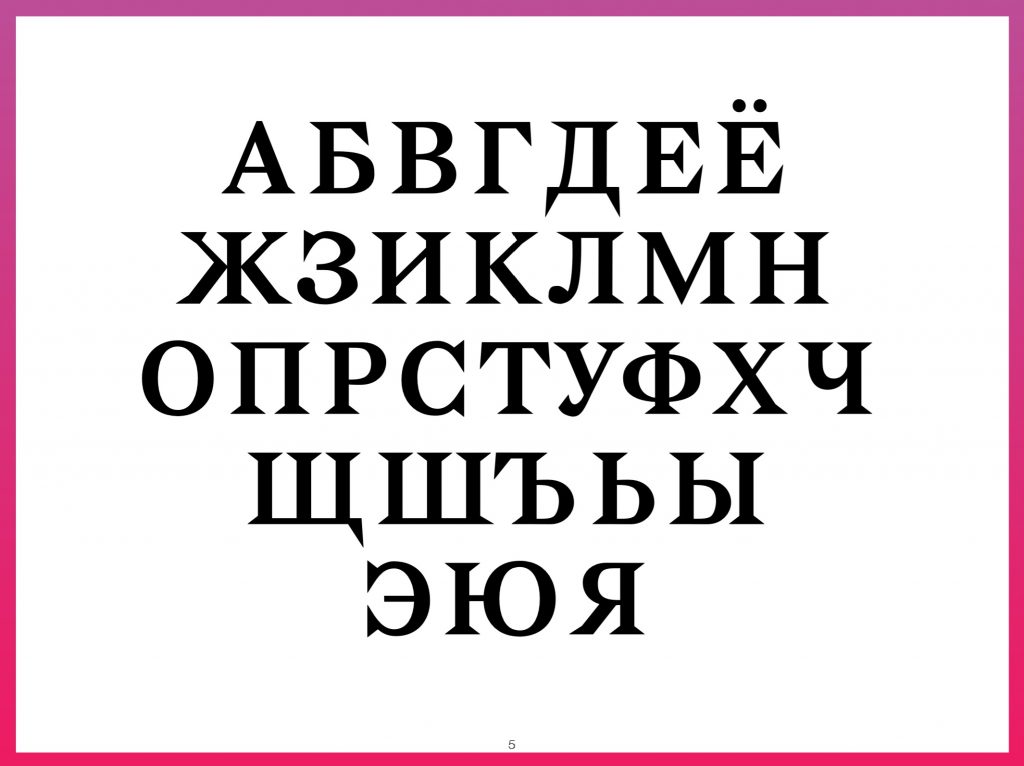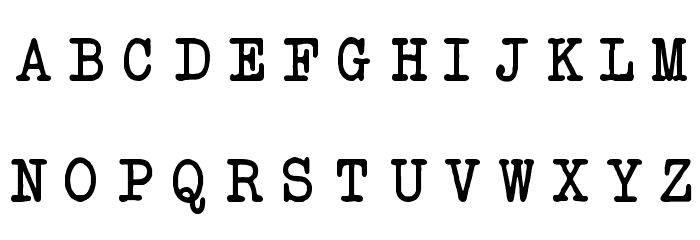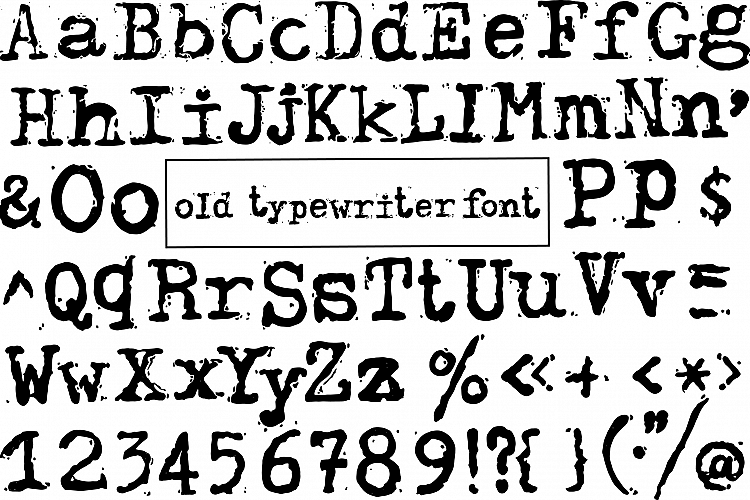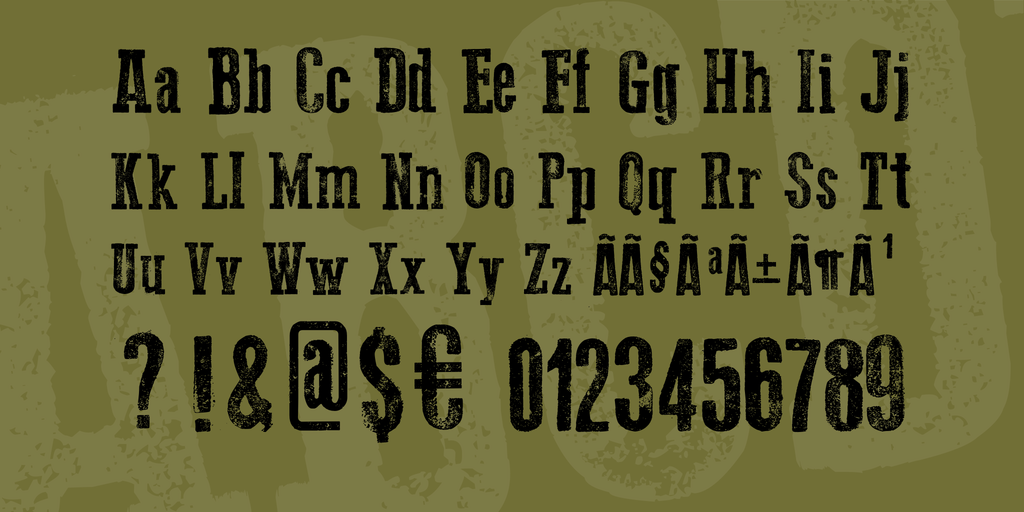
Кириллица печатная машинка шрифт: Кириллические шрифты в стиле «печатной машинки» для Photoshop
45+ шрифтов «печатная машинка» для Word / Фотошопа + машинописные русские шрифты
Название сегодняшних материалов в подборке полностью определяется способом их создания — это шрифты печатной машинкой. Теоретически, по форме и стилистике они должны соответствовать реально напечатанным текстам. Похожий принцип типографики встречался в заметках про граффити или надписи мелом на доске — по данным наименованиям вы сразу четко представляете их внешний вид.
Если говорить о визуальной составляющей, то тут все достаточно тривиально. В целом нет такого разнообразия как в декоративных и оригинальных шрифтах. Варианты отличаются разве что качеством / силой «оттиска» для букв и наличием неких посторонних «вкраплений»: где-то текст получается более четкий, в других случаях он выглядит слабо пропечатанным.
Brother Deluxe 1350
1942 Report
Special Elite
Urania Czech Font
My Underwood Font
Tox Typewriter
Through the Night
Typical Writer Font
Kingthings Typewriter
Traveling Typewriter
Rough Typewriter
CarbonType
Harting
Secret Typewriter
Courier Prime
DK Trashtype Font
Love Letter TW
AFL Font Pespaye Nonmetric
Veteran Typewriter
Есть варианты машинописных шрифтов, которые имеют чуть больше декоративных элементов.![]()
NelsonOldNewsPaper Font
Telegraphem
Old printing press
Subway Novella
Punkbabe
Xerography Font
F25 Blackletter Typewriter
Type Keys
Дополнительно нашли немного кириллических фонтов для рунета. К сожалению, оригинальных картинок с их применением здесь не так много, поэтому размещаем скриншоты с доступными символами алфавита — это даст понимание используемого в них стиля. Очевидно, что машинописных шрифтов на русском гораздо меньше англоязычных, но с десяток точно наберется.
TrixieCyr Plain
Bezpredmetizm
DS Moster
B52
a_OldTyperNr Regular
DS VTCorona Cyr
ABC_TypeWriterRussian
Lettera Trentadue
TypeWriter Normal
Prestige-Normal Regular
Vector Old Typewriter Font
Vintage Grunge Typewriter Letters
Alphabet 5 Variations of Every Letter
Typewriter Text on an Aged Paper
Type Writer Alphabet Handmade Letters
Vector Old Typewriter Font
Font Printed on Vintage Typewriter
ABCD Letters Written with a Typewriter
как распознать шрифт на пишущей машинке
Если у вас есть печатная машинка, хорошо бы знать, каким шрифтом она печатает. Я предлагаю поговорить о машинописной шрифтологии.Типографисты, описывая шрифты и их «поведение» в тексте, обычно выражаются сложными терминами: «кегль», «шпация», «интерлиньяж», «апроши», «полуапроши», а когда они говорят о размерах шрифта, они сообщают о неких пунктах, математическое значение которых, кажется, понятно только избранным.
Для начала подчеркнём одну очень важную вещь: машинописные шрифты коренным образом отличаются от типографских, так что и принцип их измерения соответствующий. Шрифт академический полужирный узкий(Типографские шрифты, материалы и принадлежности. Союзполиграфпром. М., 1950.) В прежние докомпьютерные времена полоса набора (часть страницы, отведённая под текст) складывалась из отдельных литер — металлических брусочков с зеркальными формами букв и других символов. Отсылка к металлическому набору может показаться устаревшей, но на самом деле современные дизайнеры и верстальщики до сих пор, часто сами того не осознавая, мыслят теми же категориями брусковых литер. Составление печатной формы при помощи набора брусковых литер
University Creative Services Photography Металлический набор не только определил многие особенности современных шрифтов, но и продолжает влиять на процесс их разработки и применения.
Дело не только в традиции. За столетия развития книгопечатания правила и принципы оформления текстов довели до совершенства, если теперь и можно выдумать что-то новое, это скорее будет претендовать на уровень «фишки», но никак на гениальность.LTS Rare Базовым понятием в типографском шрифте является кегль – размер высоты буквы или знака, включая нижние и верхние выносные элементы и заплечики.Заплечики – невидимая область, но они со времён металлического набора влияют на размер знака по сию пору. При ручном наборе благодаря этим заплечикам создавался минимальный интерлиньяж — междустрочное расстояние (чтобы увеличить интерлиньяж использовался шпон — специальный пробельный материал, пластина). Как правило, кегль измеряется в традиционных полиграфических единицах — пунктах. В европейской (и российской) системе 1 пункт равен 0,3759 мм, в англо-американской — 0,3528 мм (1/72 дюйма).